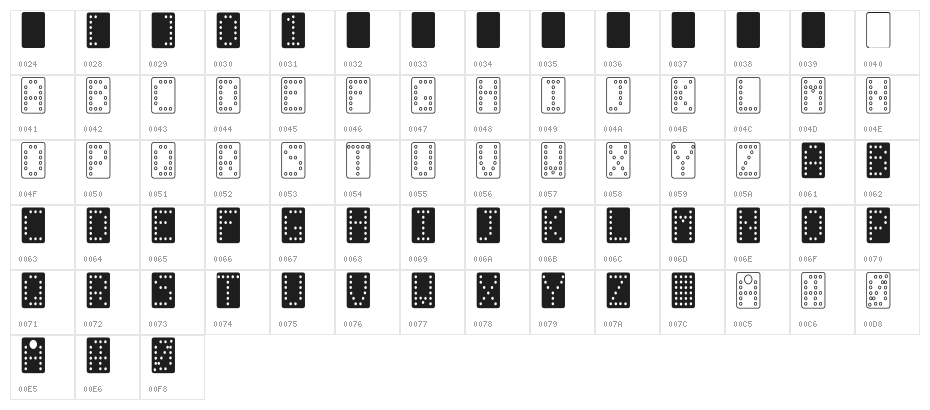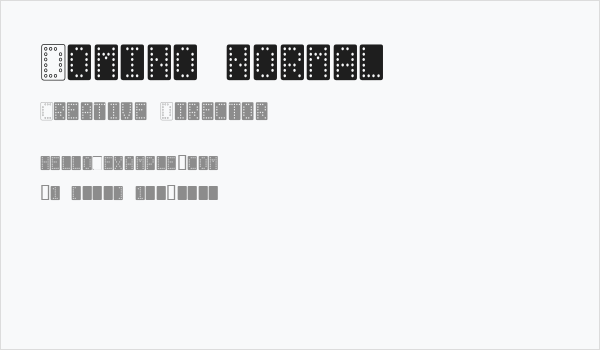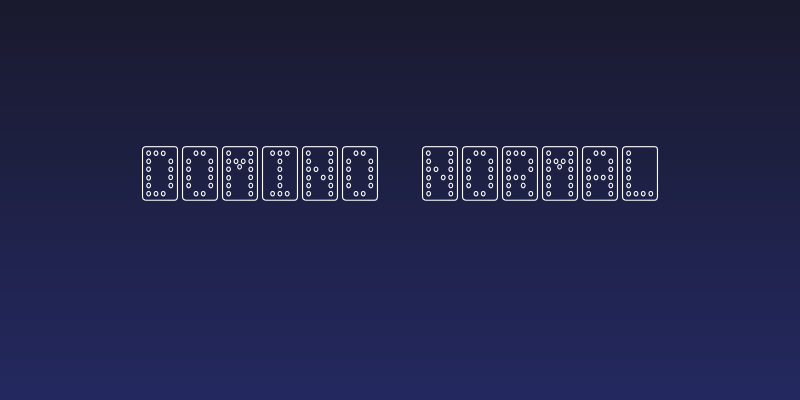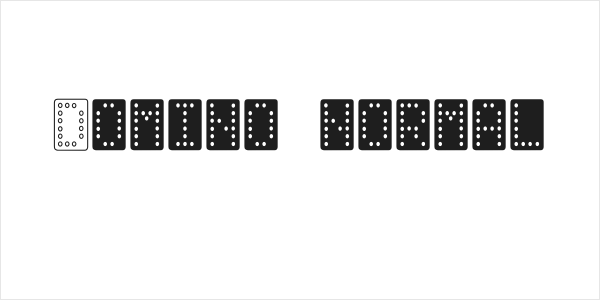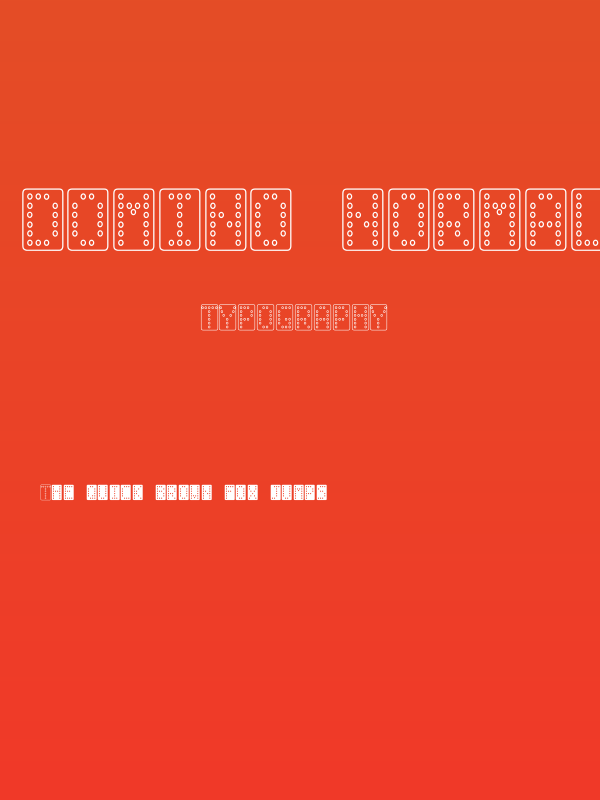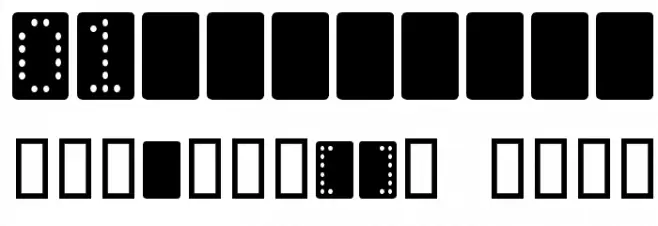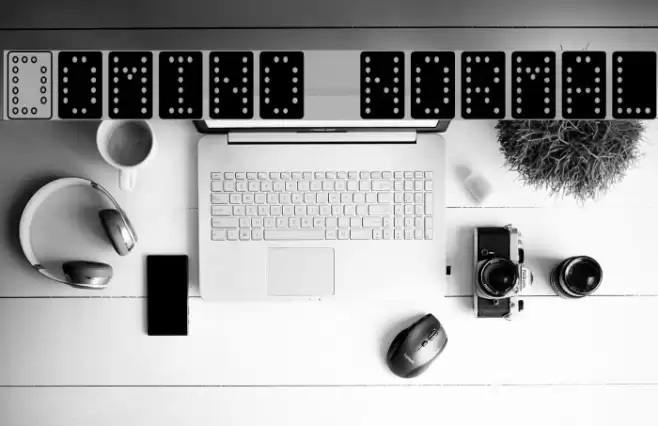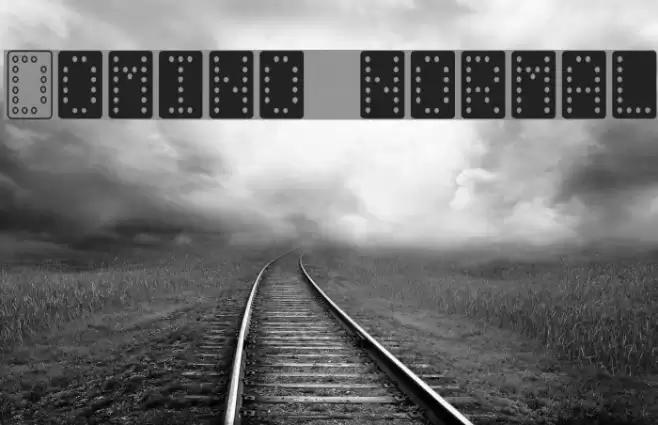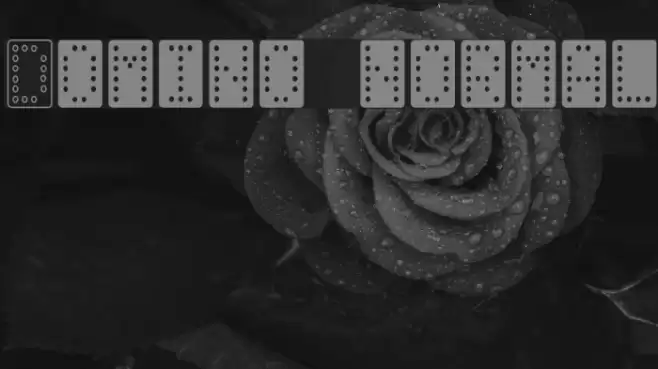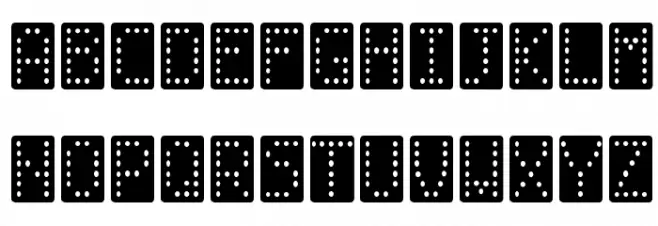
Domino normal Font
| Style général | Playful, Creative |
| Cas d'utilisation | Logos, Posters, Creative Displays |
| Projets proposés | Ideal for game-themed designs, children's books, playful branding, and creative posters. |